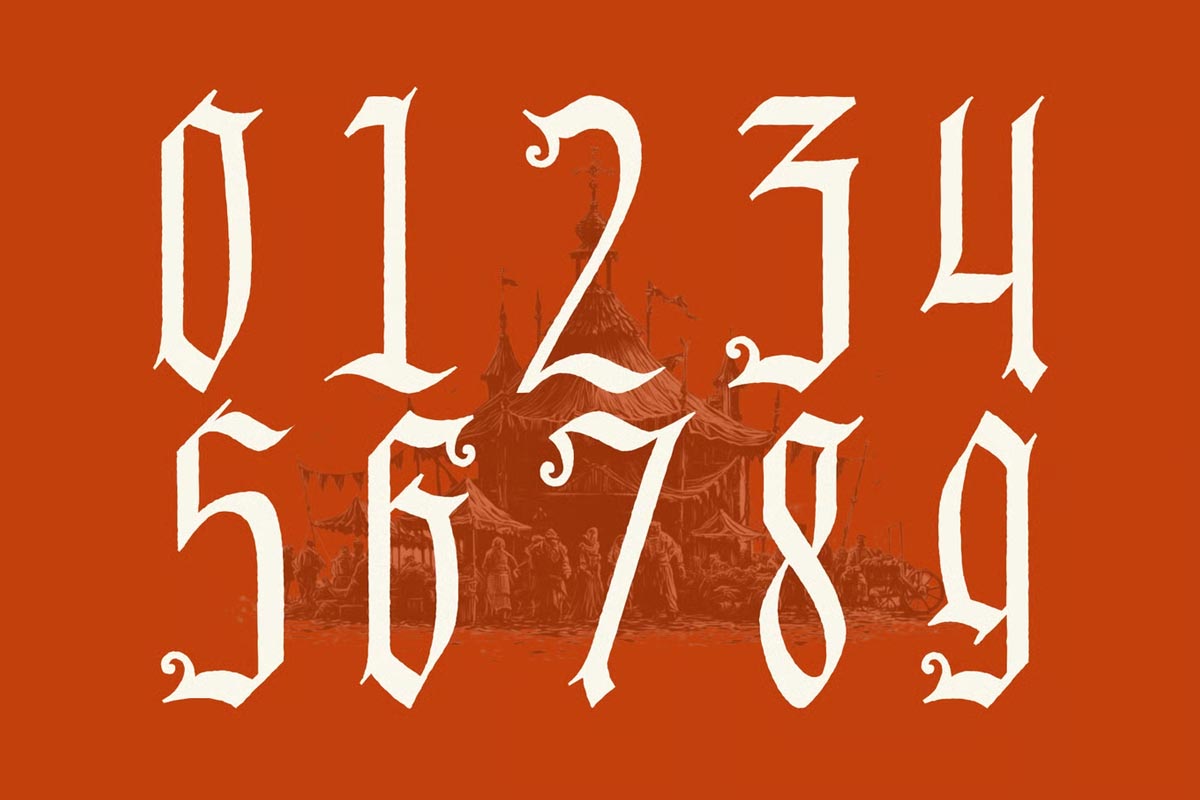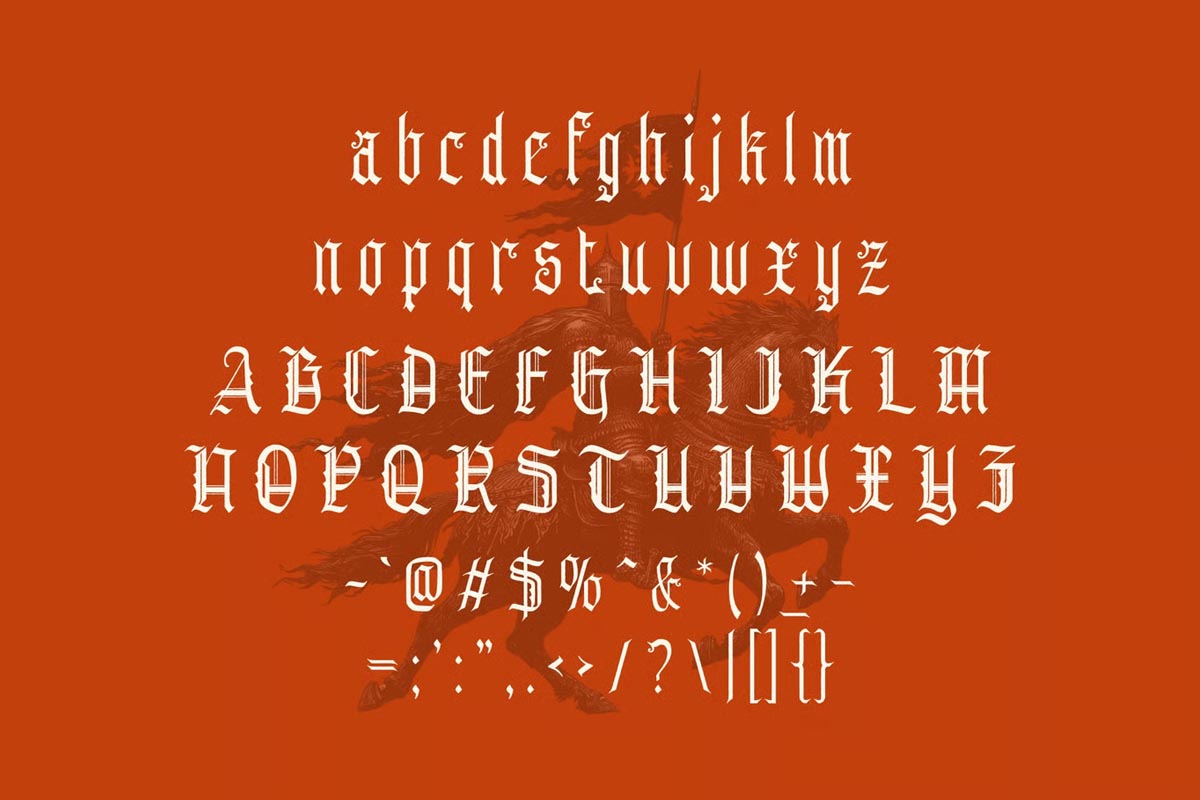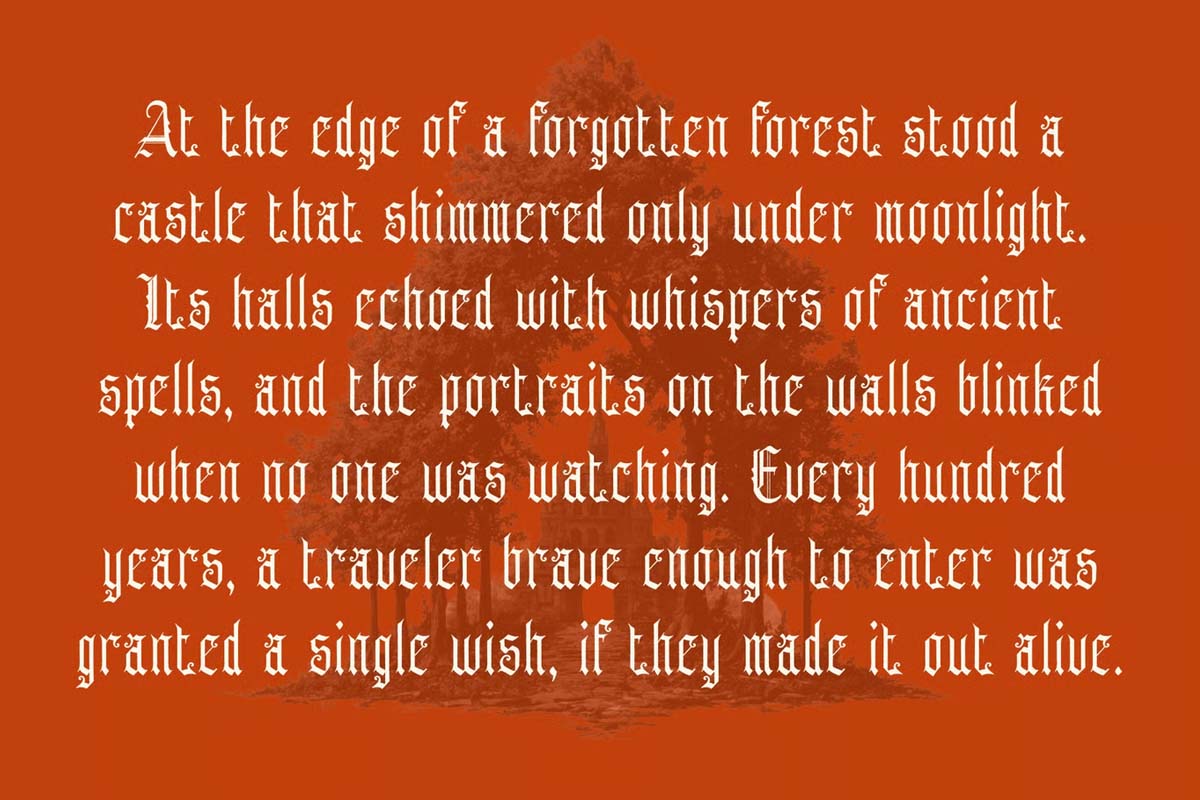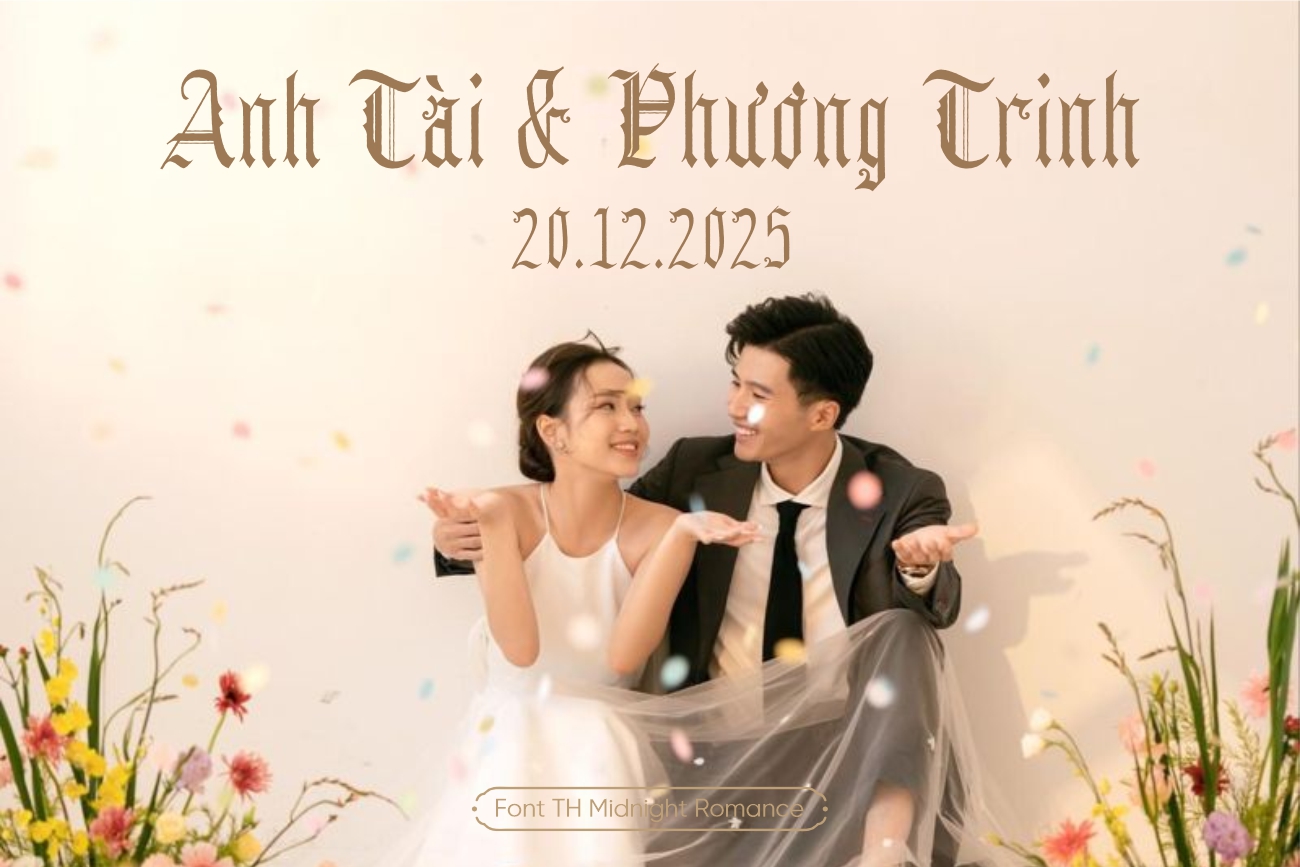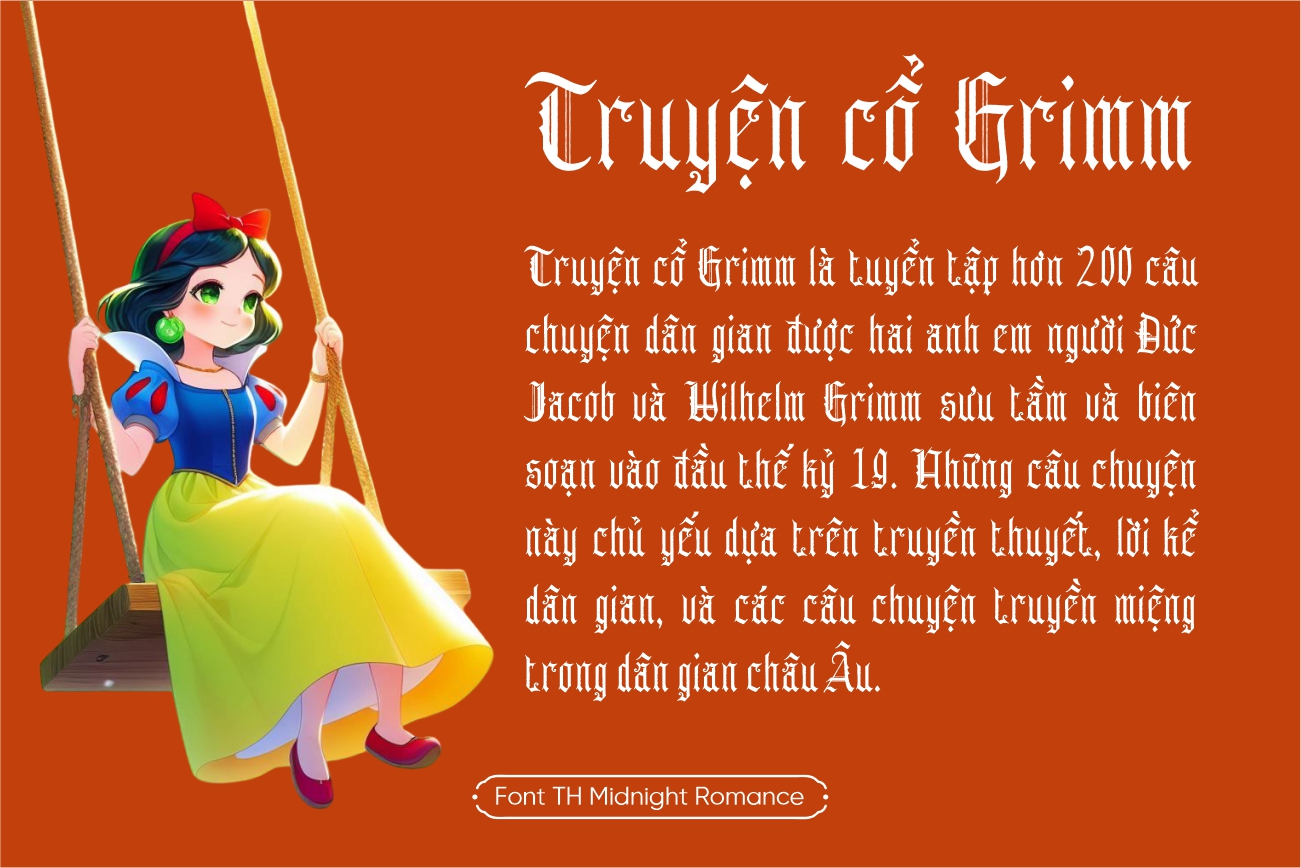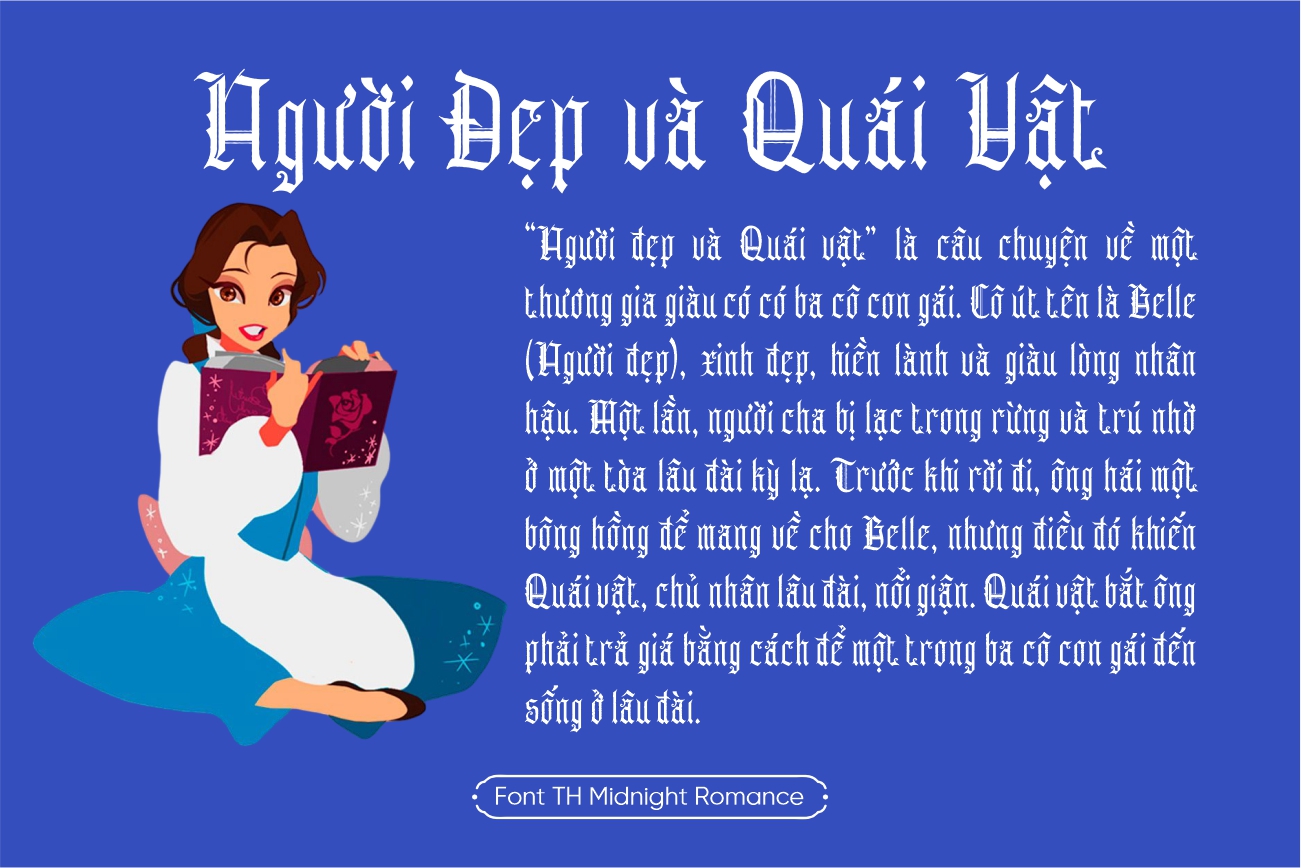
Font Chữ Gothic Huyền Bí và Thanh Lịch TH Midnight Romance Việt Hóa
Nguồn gốc và Tác giả Midnight Romance nguyên bản là một sáng tạo độc đáo của epdesigns, một nhà thiết kế nổi tiếng trên nền tảng Envato Elements. Được sinh ra từ niềm đam mê với những con chữ thời trung cổ, bộ font này không chỉ đơn thuần là công cụ soạn thảo mà là một tác phẩm nghệ thuật kỹ thuật số. Nhận thấy vẻ đẹp và tiềm năng ứng dụng cao của nó tại thị trường Việt Nam, Team TH đã dày công nghiên cứu và thực hiện bản Việt hóa hoàn chỉnh. Việc việt hóa một font chữ Gothic với nhiều chi tiết phức tạp là một thách thức không nhỏ, nhưng Team TH đã xử lý khéo léo các dấu câu tiếng Việt để đảm bảo chúng hòa quyện hoàn hảo với cấu trúc ký tự gốc, giữ nguyên linh hồn của thiết kế ban đầu.
Phong cách thiết kế Midnight Romance thuộc dòng Blackletter (Gothic) nhưng lại mang một hơi thở hoàn toàn khác biệt: "Elegant Gothic" – Gothic thanh lịch. Khác với sự thô ráp, nặng nề thường thấy của các font chữ kim loại hay rock, Midnight Romance sở hữu những đường nét serif sắc sảo nhưng vô cùng tinh tế. Lấy cảm hứng từ những tờ báo cũ kỹ và các bản thảo viết tay trong tu viện cổ xưa, font chữ này gợi lên cảm giác hoài niệm, ma mị và đầy kịch tính.
Từng ký tự được trau chuốt với độ tương phản cao giữa nét thanh và nét đậm, tạo nên nhịp điệu thị giác vừa cổ điển vừa sang trọng. Đây là sự lựa chọn hoàn hảo cho phong cách Dark Academia, các bìa tiểu thuyết giả tưởng (fantasy), poster phim kinh dị, hoặc các dự án branding cần sự uy nghiêm và bí ẩn. Với bản Việt hóa từ Team TH, các nhà thiết kế Việt giờ đây có thể thỏa sức kể những câu chuyện nhuốm màu huyền thoại bằng ngôn ngữ mẹ đẻ mà không lo bị lỗi font hay mất đi tính thẩm mỹ vốn có.